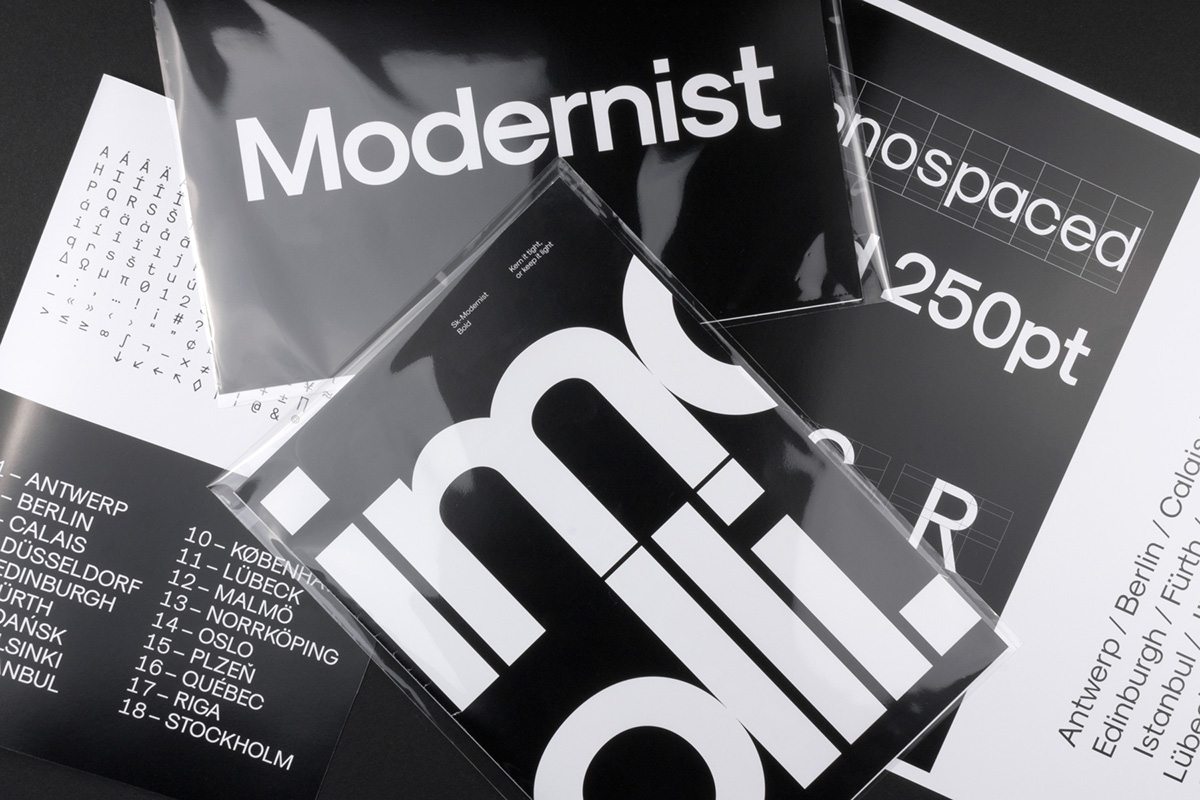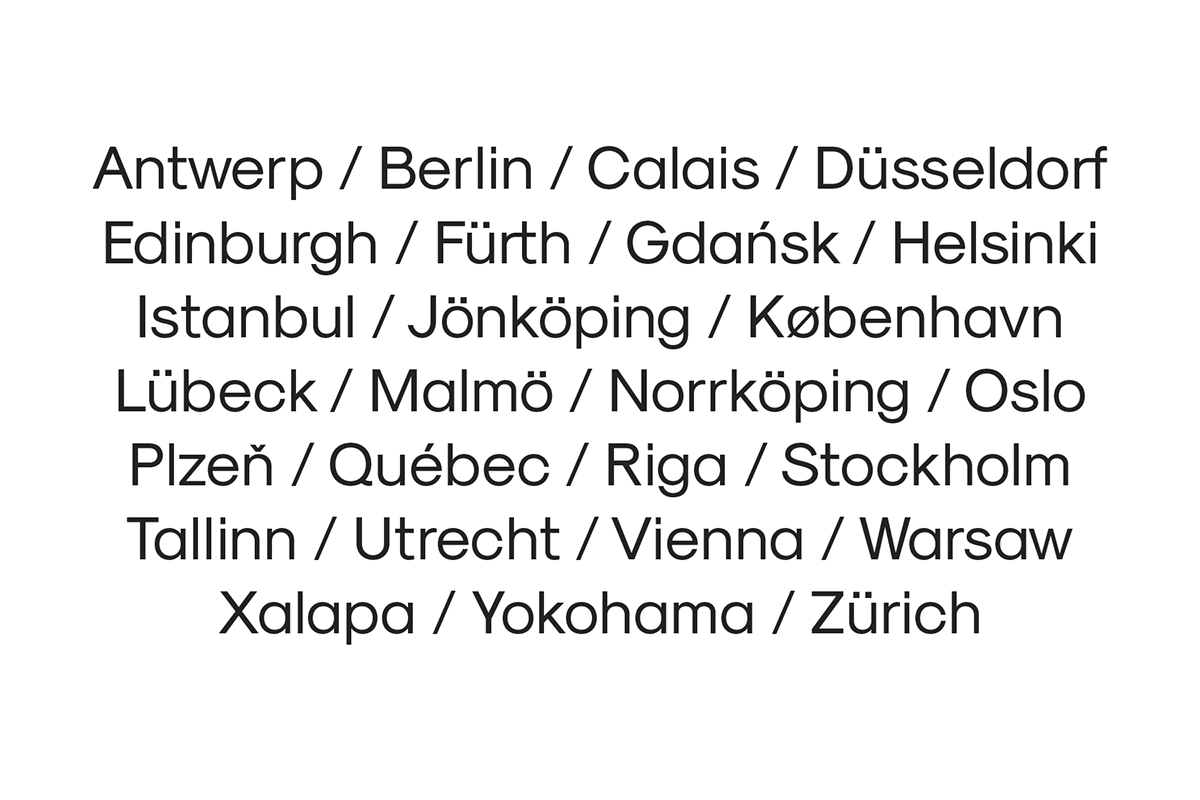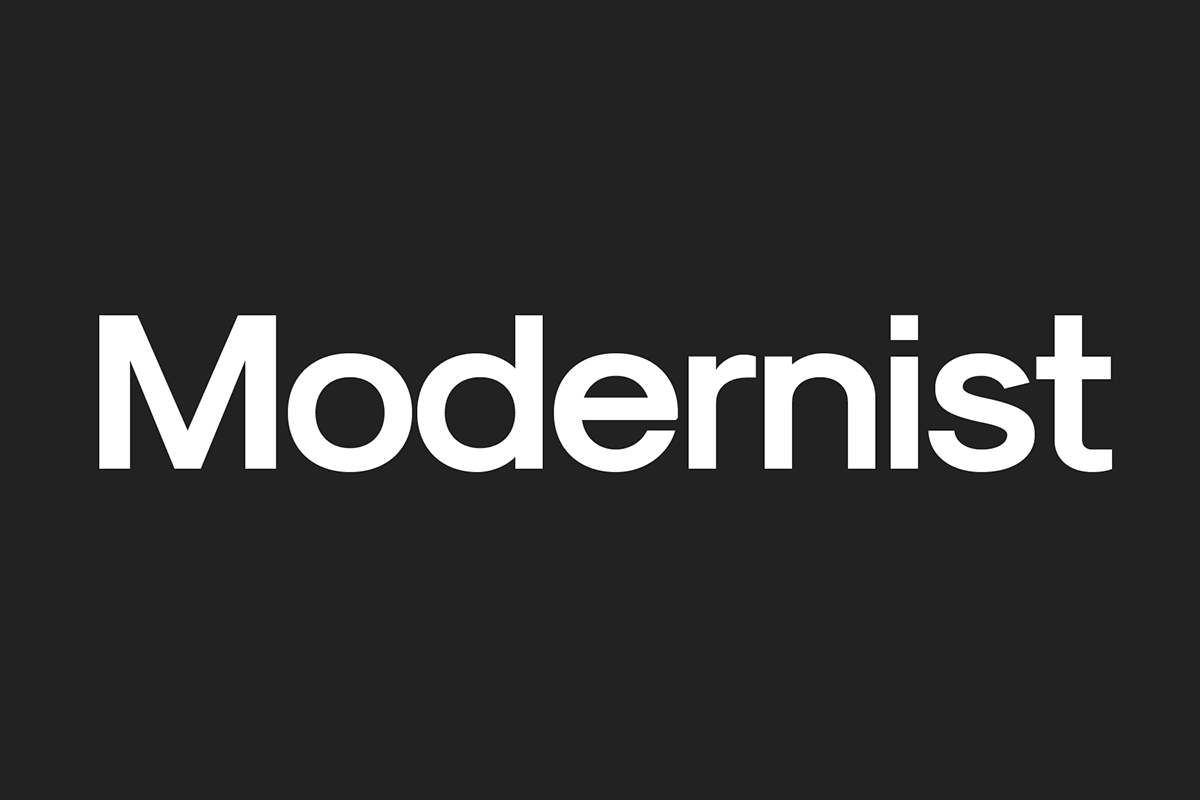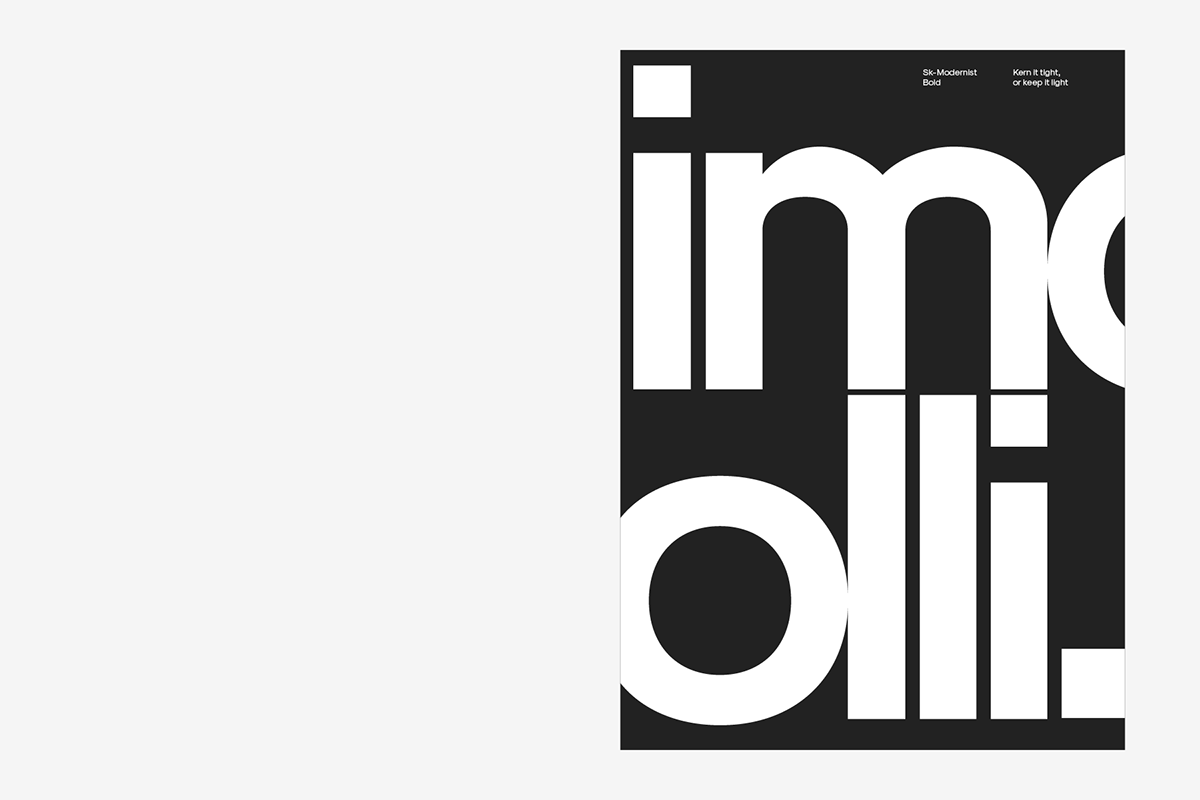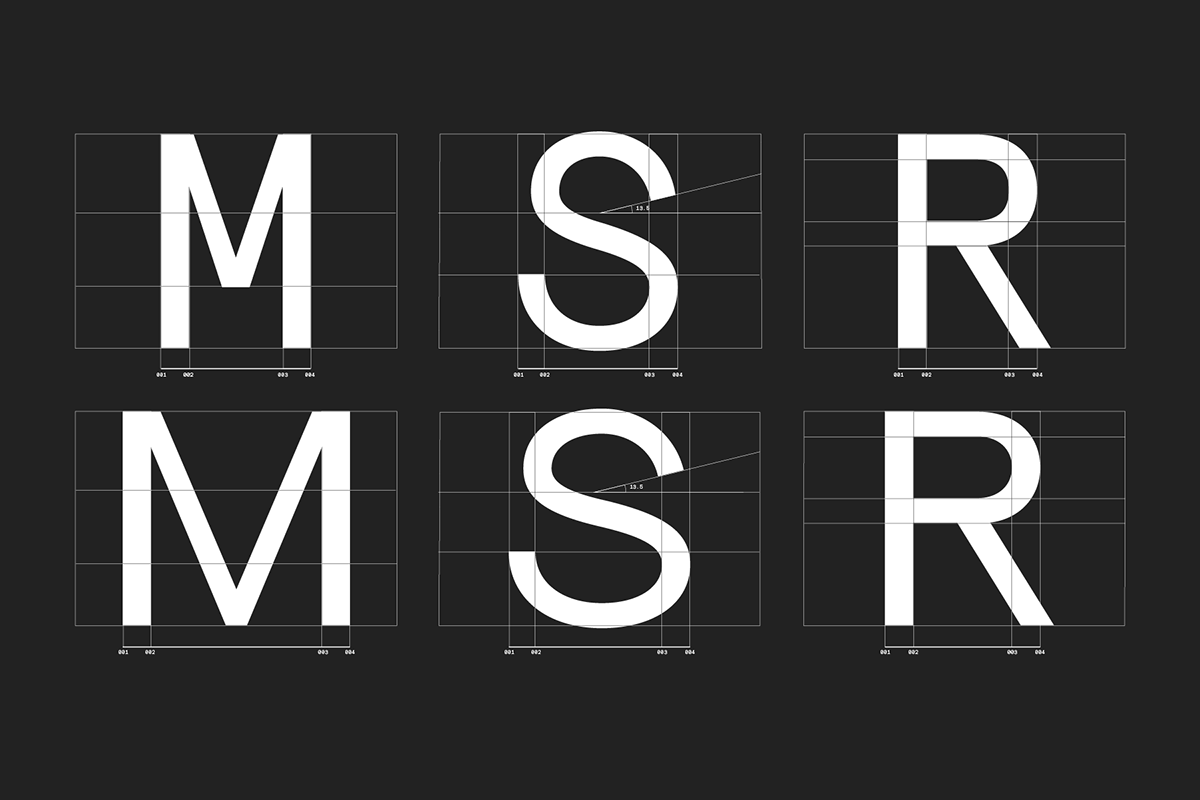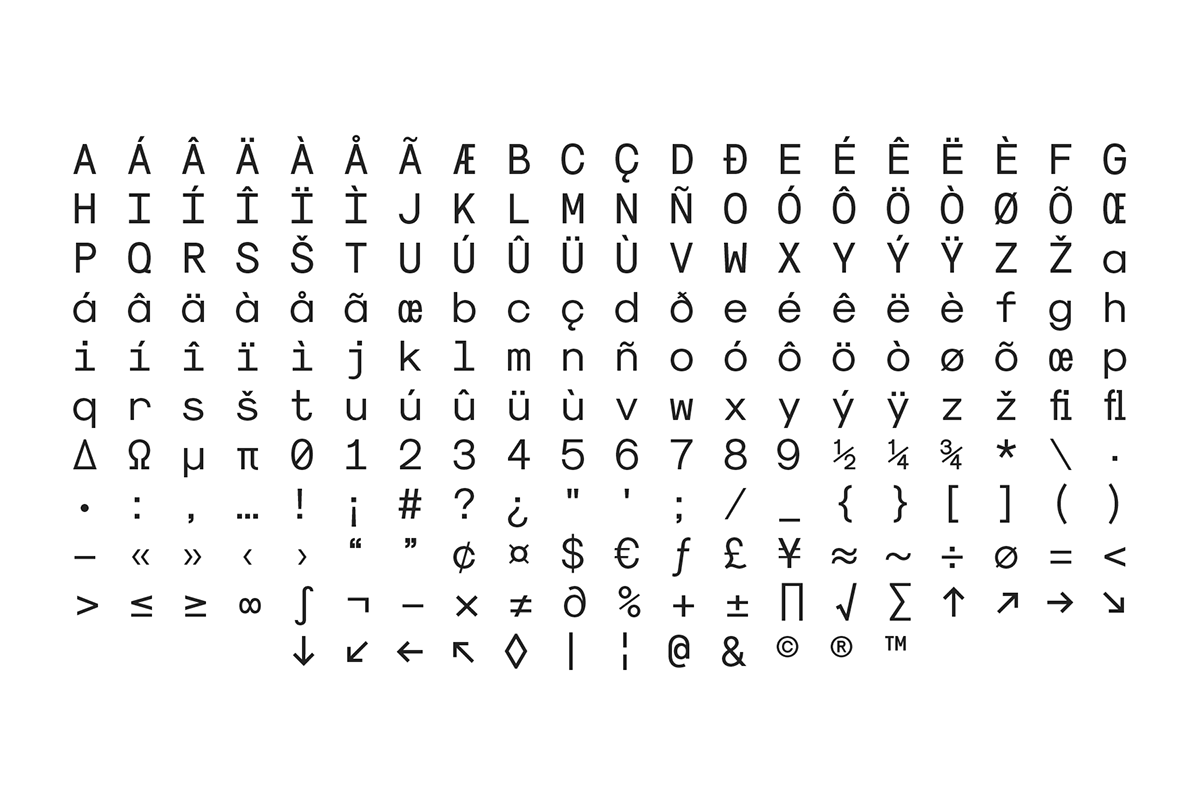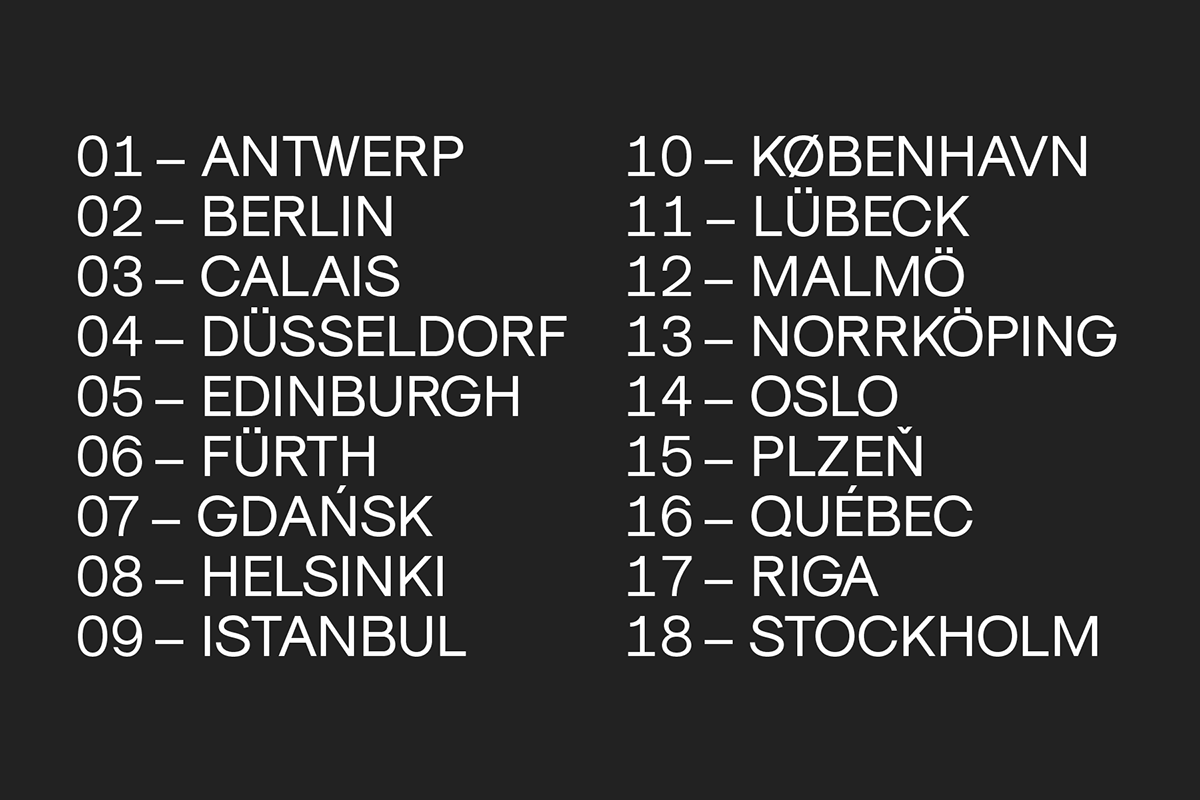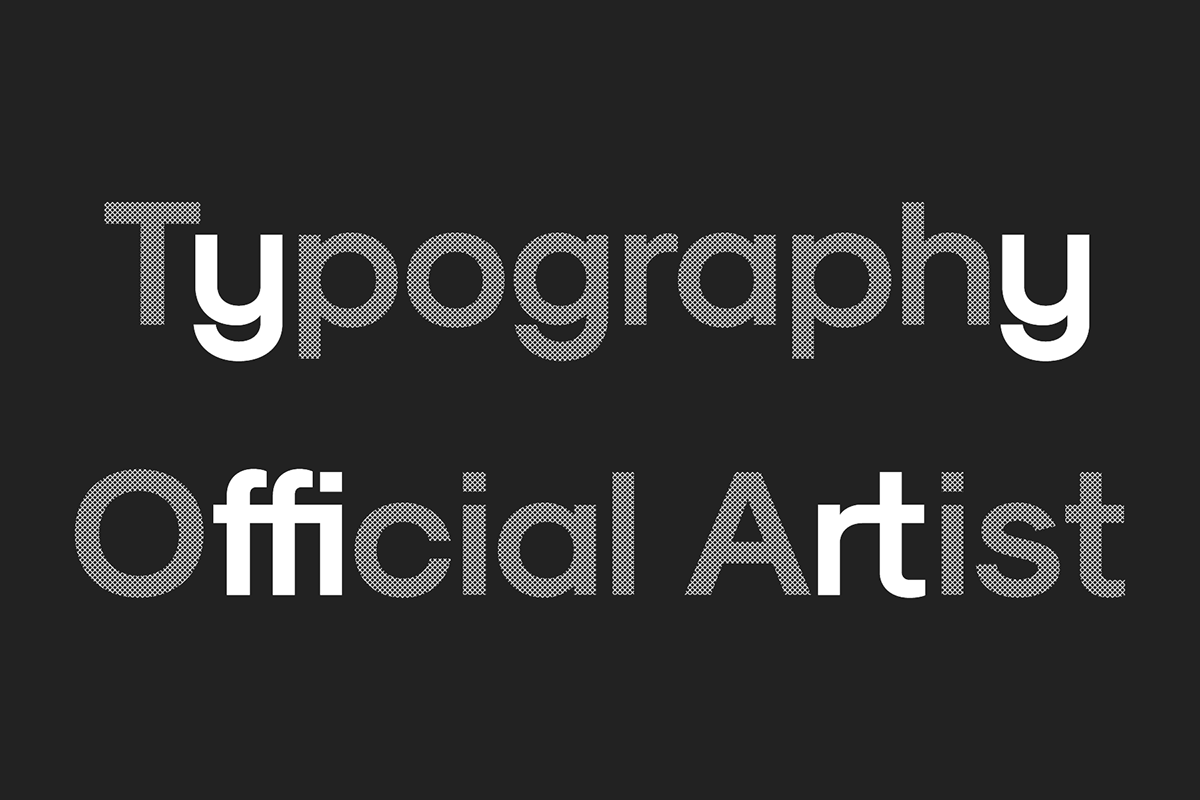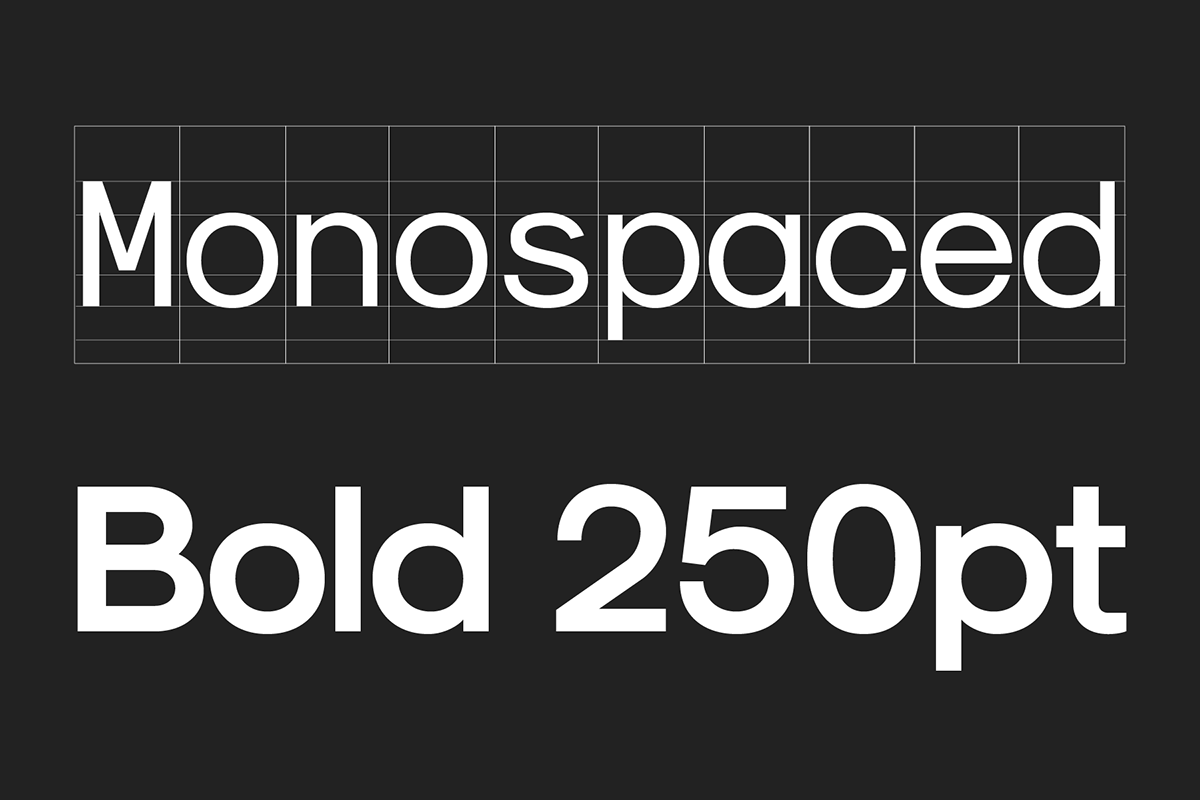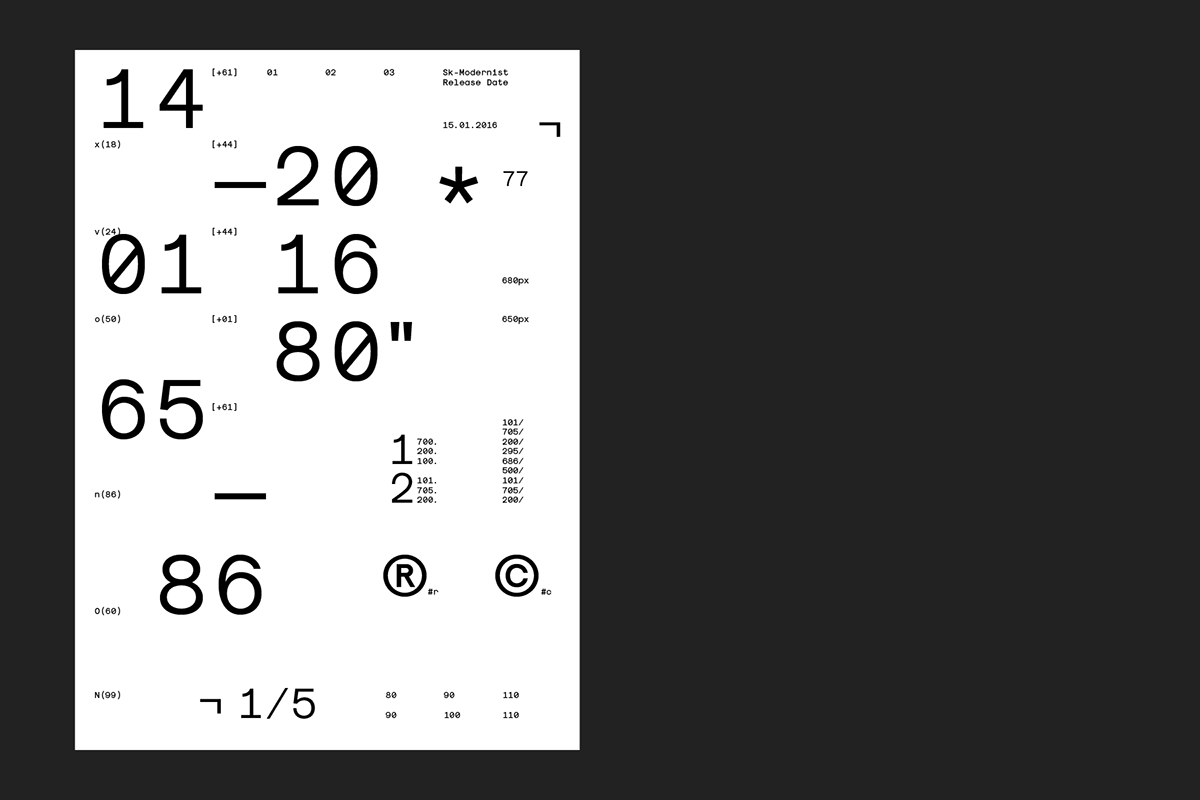
font del giorno: MODERNIST
il font che vi presentiamo oggi é: Sk-Modernist
Sk–modernista è un carattere minimalista e pulito, che rifugge le  forme e le grazie complicate. Lo scopo del carattere era quello di creare un amalgama di un moderno Grotesk , come l’Helvetica, con uno stile geometrico semplice, come l’Avant Garde.